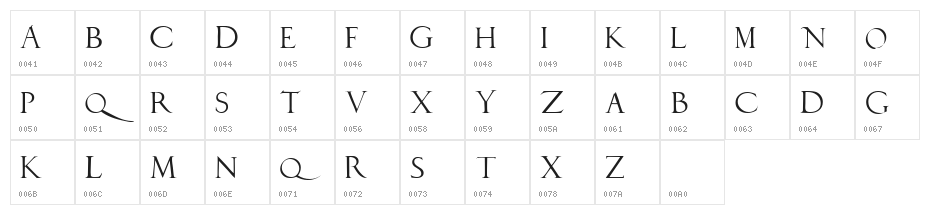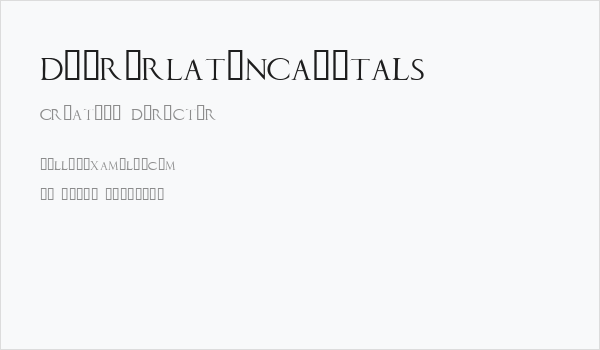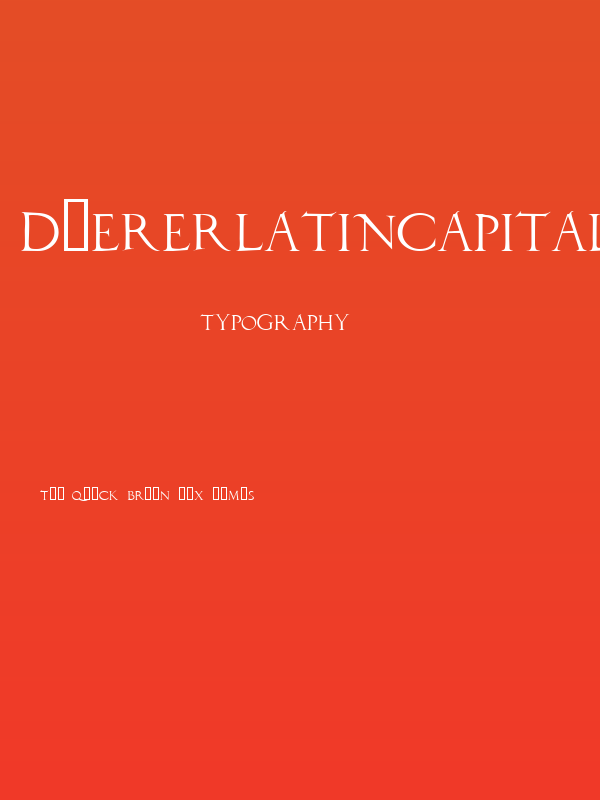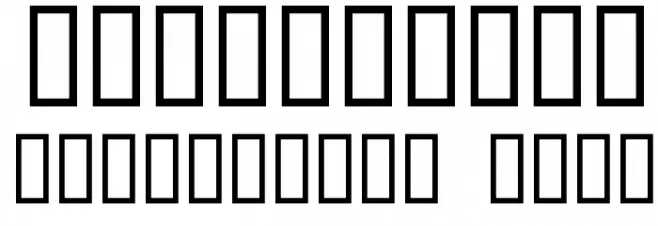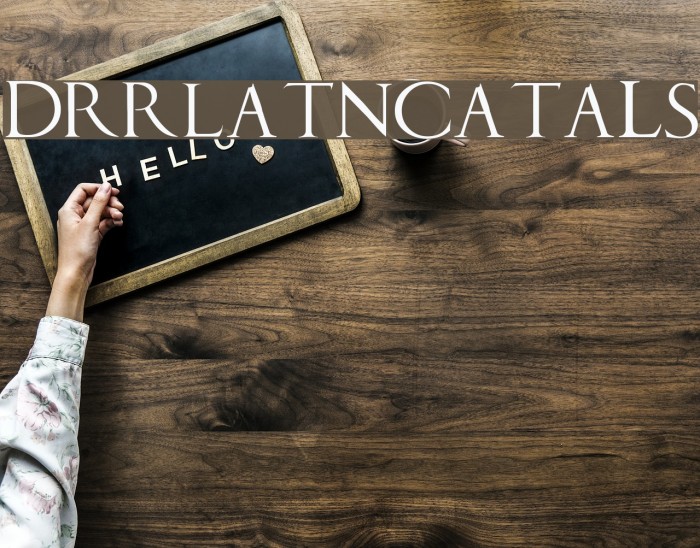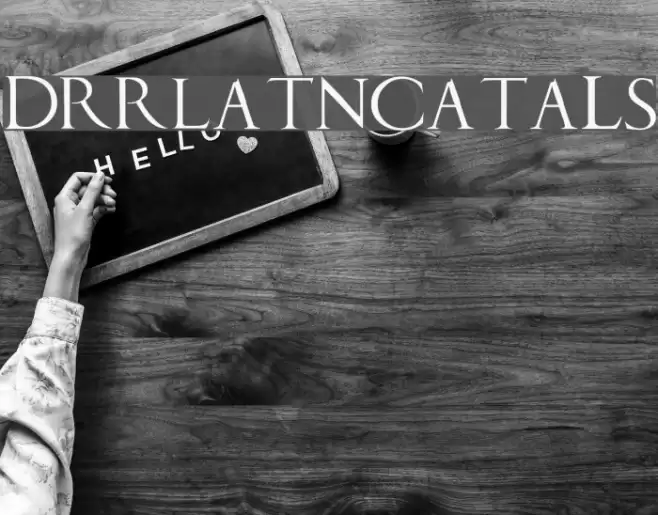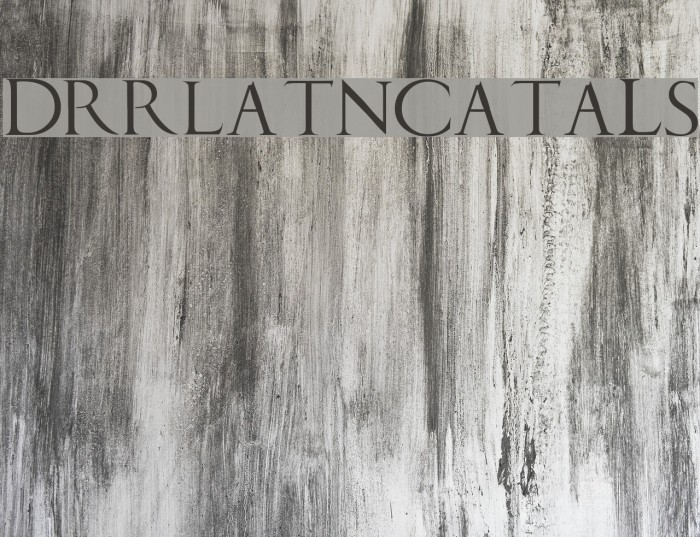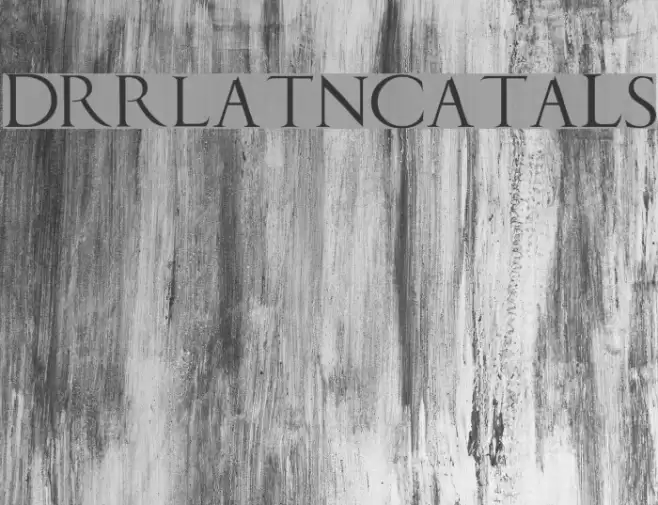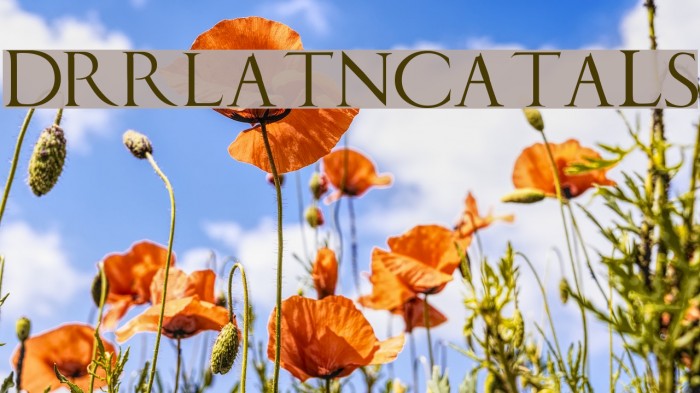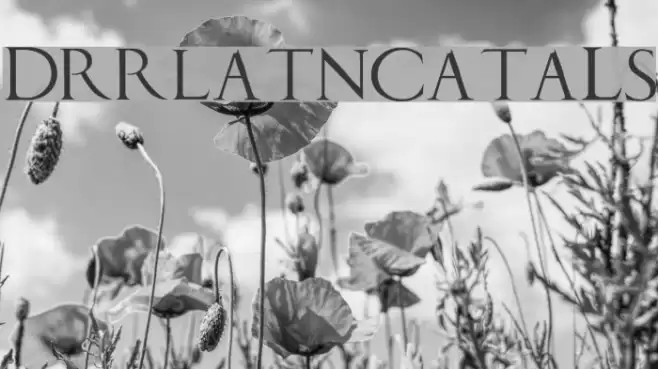
DuererLatinCapitals Font
| おすすめプロジェクト | Ideal for use in formal invitations, book covers, historical documents, and branding that requires a classic touch. |